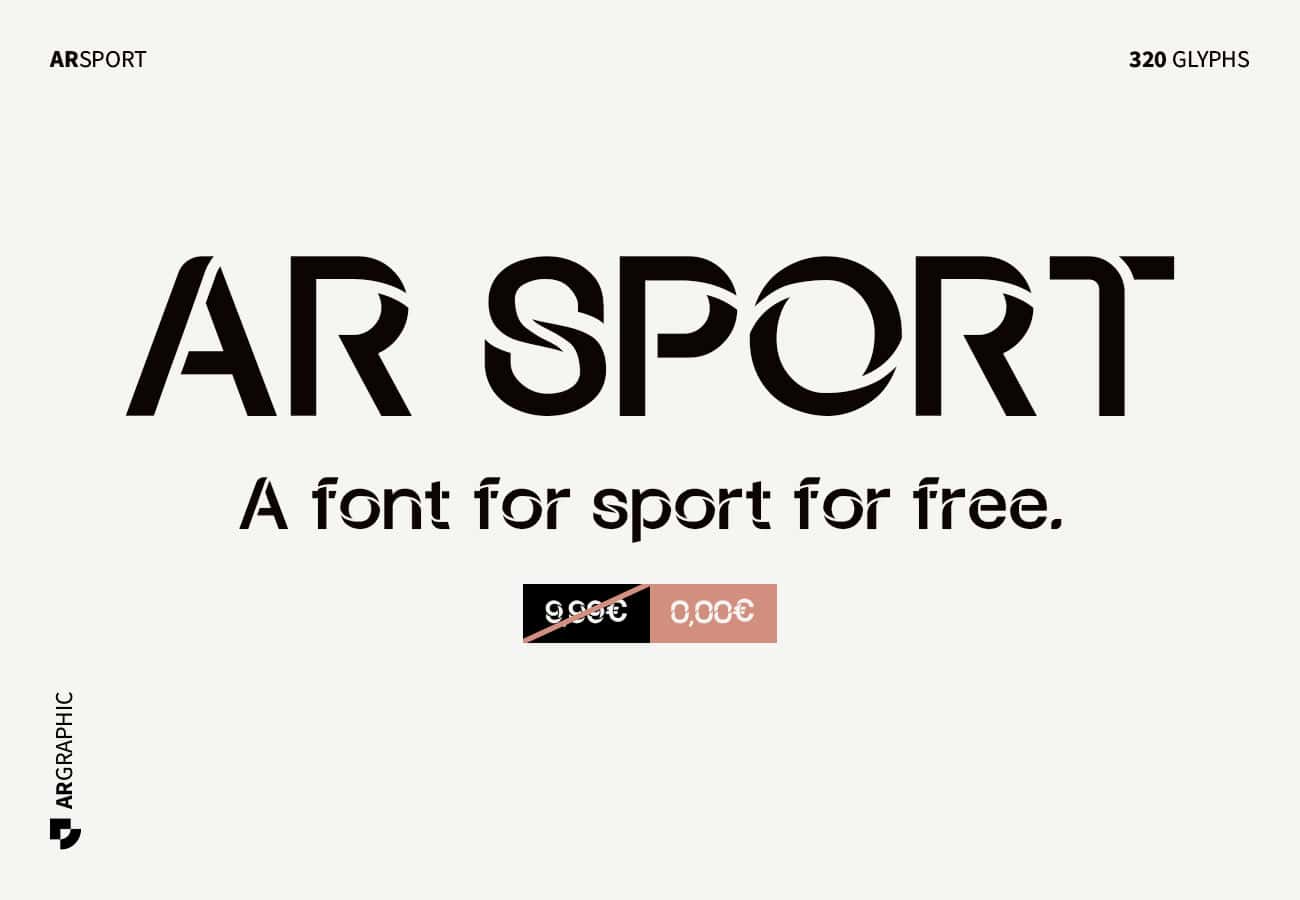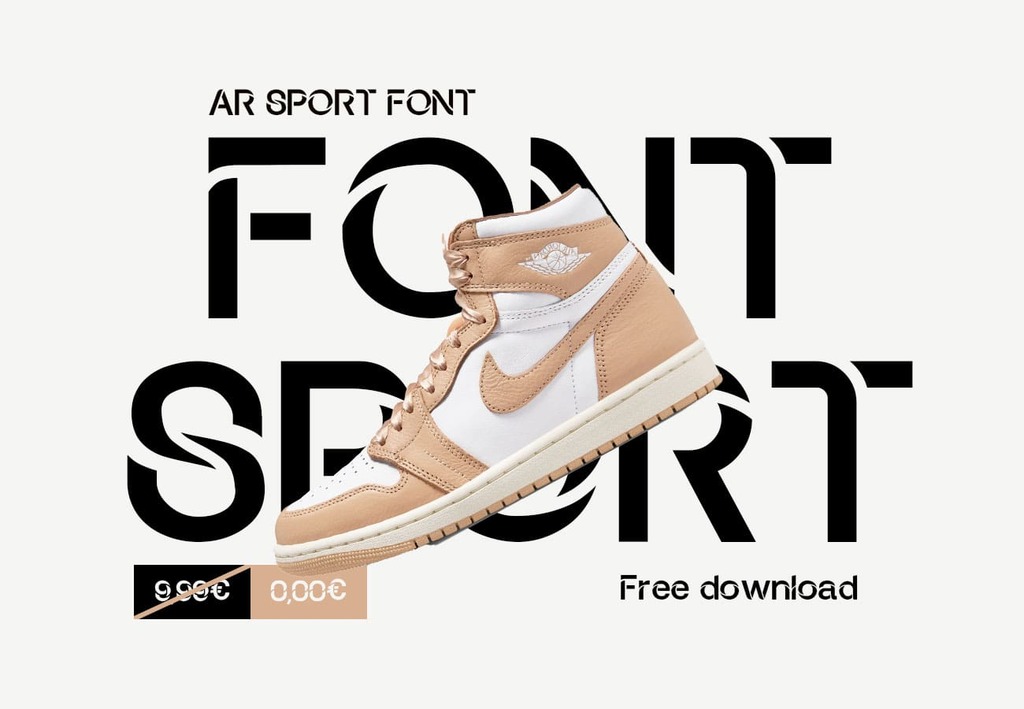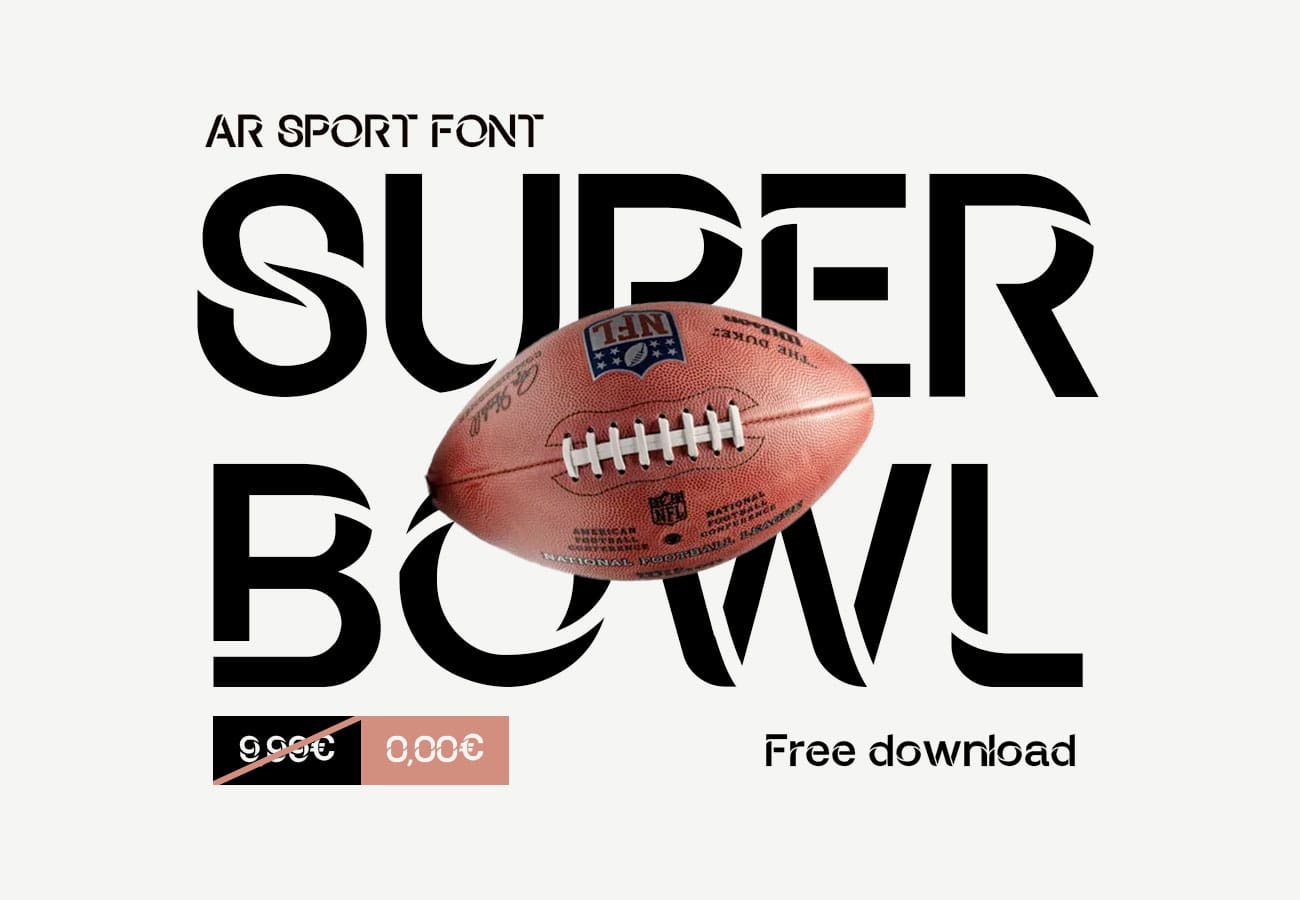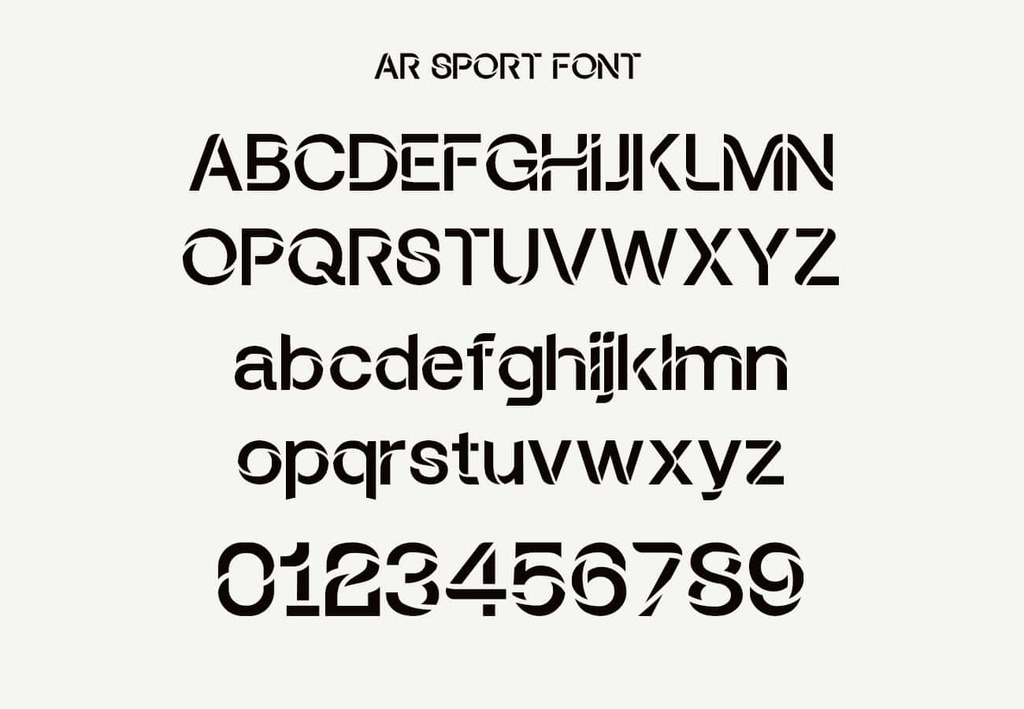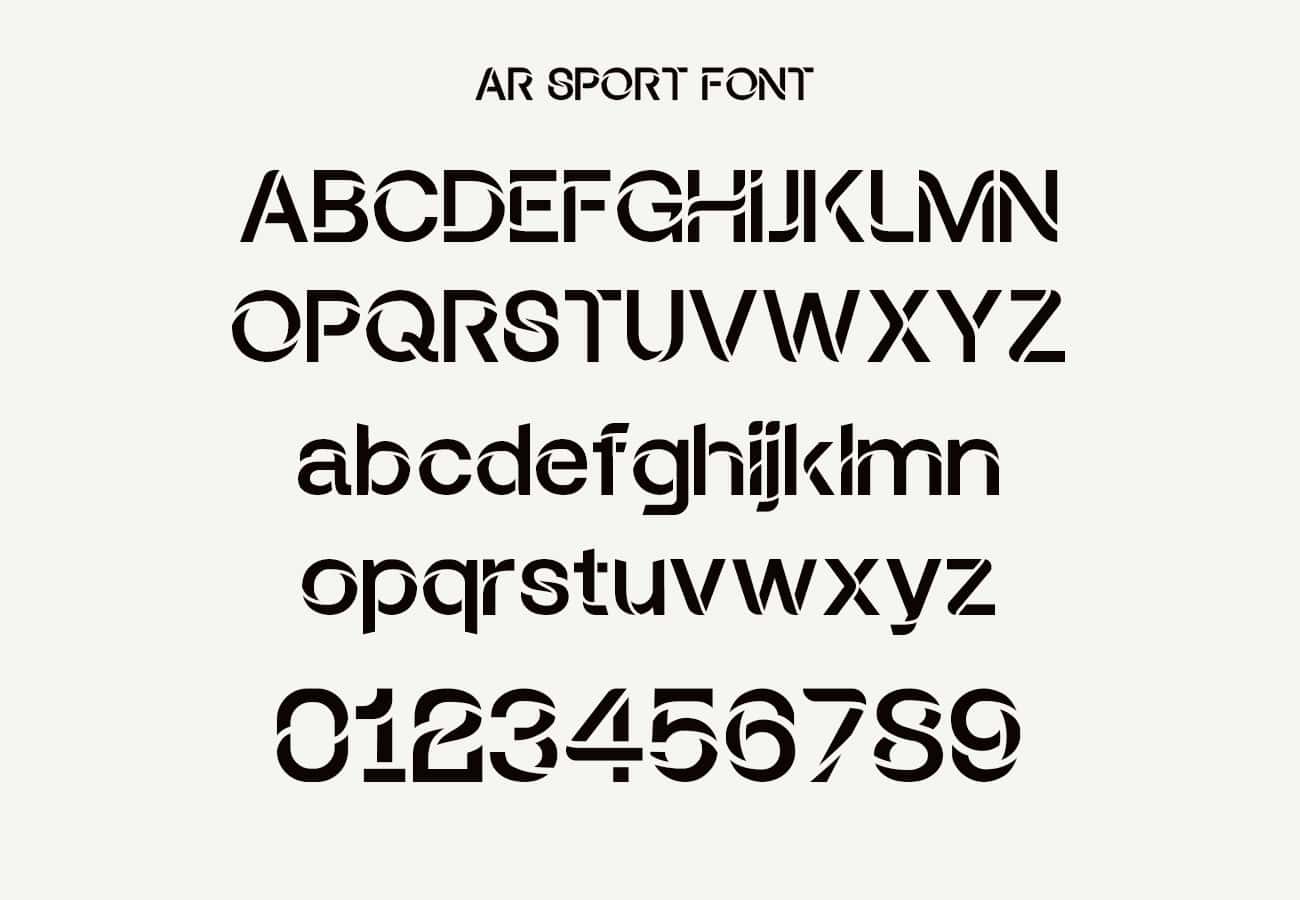
Typographie AR-Sport : la police du sport
La typographie AR-Sport offre un moyen distinctif et prégnant de mettre en valeur l’esprit sportif. Créée par l’agence de communication Argraphic, cette typographie est en effet spécialement conçue pour répondre aux besoins du monde sportif, que ce soit des logos ou des marques. Dans cet article, nous allons présenter aussi précisément que possible la typographie AR-Sport, explorer ses avantages uniques et vous révéler la façon dont vous pouvez l’obtenir gratuitement, exclusivement sur le site d’Argraphic.
Qu’est-ce que la typographie AR-Sport ?
La police AR-Sport, une forme de typographie qui intègre des éléments de mouvement pour créer des expériences visuelles dynamiques et engageantes. Cette police novatrice ajoute une dimension supplémentaire aux designs typographiques traditionnels, en les rendant interactifs et captivants.
Les avantages de la typographie AR-Sport
1. L’attractivité visuelle
La typographie AR-Sport attire immédiatement l’attention du spectateur grâce à ses effets visuels époustouflants. Les caractères semblent s’animer à l’écran, créant ainsi un impact visuel fort, ce qui est essentiel dans le monde du sport où la concurrence est féroce.
2. La prégnance visuelle
Capter l’attention au premier regard n’est pas une fin en soi. Il convient en effet de marquer les potentiels prospects sur la durée. En ce sens, cette police est parfaitement adapté au regard de la prégnance qui accompagne son esthétique.
3. Marquer une différence
Dans le monde du sport, la différenciation est essentielle. La police AR-Sport permet de se démarquer de la concurrence en offrant une solution de design unique idéale pour se singulariser.
Un must-have pour l’univers du sport
Que vous soyez une équipe sportive professionnelle, une marque liée au sport ou même un passionné cherchant à créer un logo percutant, la typographie AR-Sport offre une solution inégalée pour exprimer votre passion et votre engagement.
Embellir vos créations graphiques
La font AR-Sport offre une opportunité exceptionnelle d’embellir vos créations graphiques. Que vous soyez un designer professionnel ou un passionné du sport, vous serez émerveillé par la manière dont cette typographie peut donner vie à vos projets. Les caractères dynamiques et stylisés ajouteront une dimension esthétique unique à vos visuels qui bénéficieront alors d’un impact indéniable. Imaginez donc des affiches de match, des publicités sportives ou des logos d’équipe qui sautent aux yeux grâce à la typographie AR-Sport. Elle permet ainsi de capturer l’essence même de l’action sportive, ajoutant une touche de magie visuelle à vos créations.
Créez des designs saisissants
Avec la police de caractère AR-Sport, vous avez le pouvoir de créer des designs saisissants qui resteront gravés dans l’esprit de votre public. Les possibilités de personnalisation sont infinies, vous permettant d’adapter la typographie à votre vision créative. Que vous souhaitiez transmettre la puissance d’une équipe de football, l’élégance du tennis ou l’adrénaline du skateboard, la Typographie AR-Sport s’adapte à chaque discipline sportive. Créez des designs qui résonnent avec passion et émotion, et laissez une empreinte indélébile dans le monde du sport et au-delà. La police AR-Sport est bien plus qu’une simple police de caractères, c’est une expérience visuelle qui vous permet de raconter des histoires captivantes grâce à vos designs.
La typographie AR-Sport représente un atout précieux dans le domaine de la communication visuelle sportive. Créée par l’agence de communication Argraphic, elle offre en effet des avantages significatifs en termes d’attractivité visuelle, d’engagement du public et de différenciation. Si vous cherchez à faire passer votre message sportif au niveau supérieur, n’hésitez pas à explorer cette typographie révolutionnaire. Elle vous permettra de faire ressortir la passion et l’énergie de votre sport avec une certaine élégance.